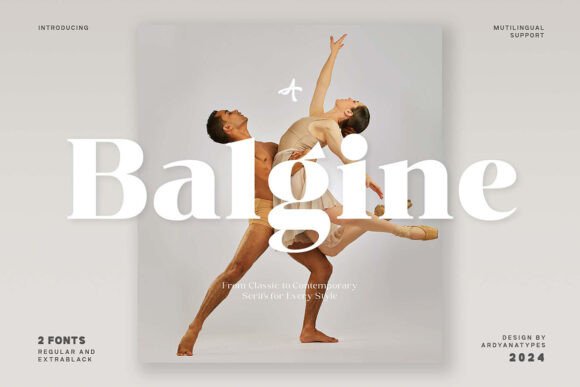
Balgine
適切なデザイン要素を見つけるのは難しい場合がありますが、Balgineは作品を即座に引き立てる優れたコレクションを提供します。
精密に作られたBalgineは、クリーンなベクター、滑らかなタイポグラフィ、そして安心のための商用ライセンスを提供します。
POD(オンデマンド印刷)製品、結婚式の招待状、またはソーシャルメディアのグラフィックを作成している場合でも、Balgineは理想的です。